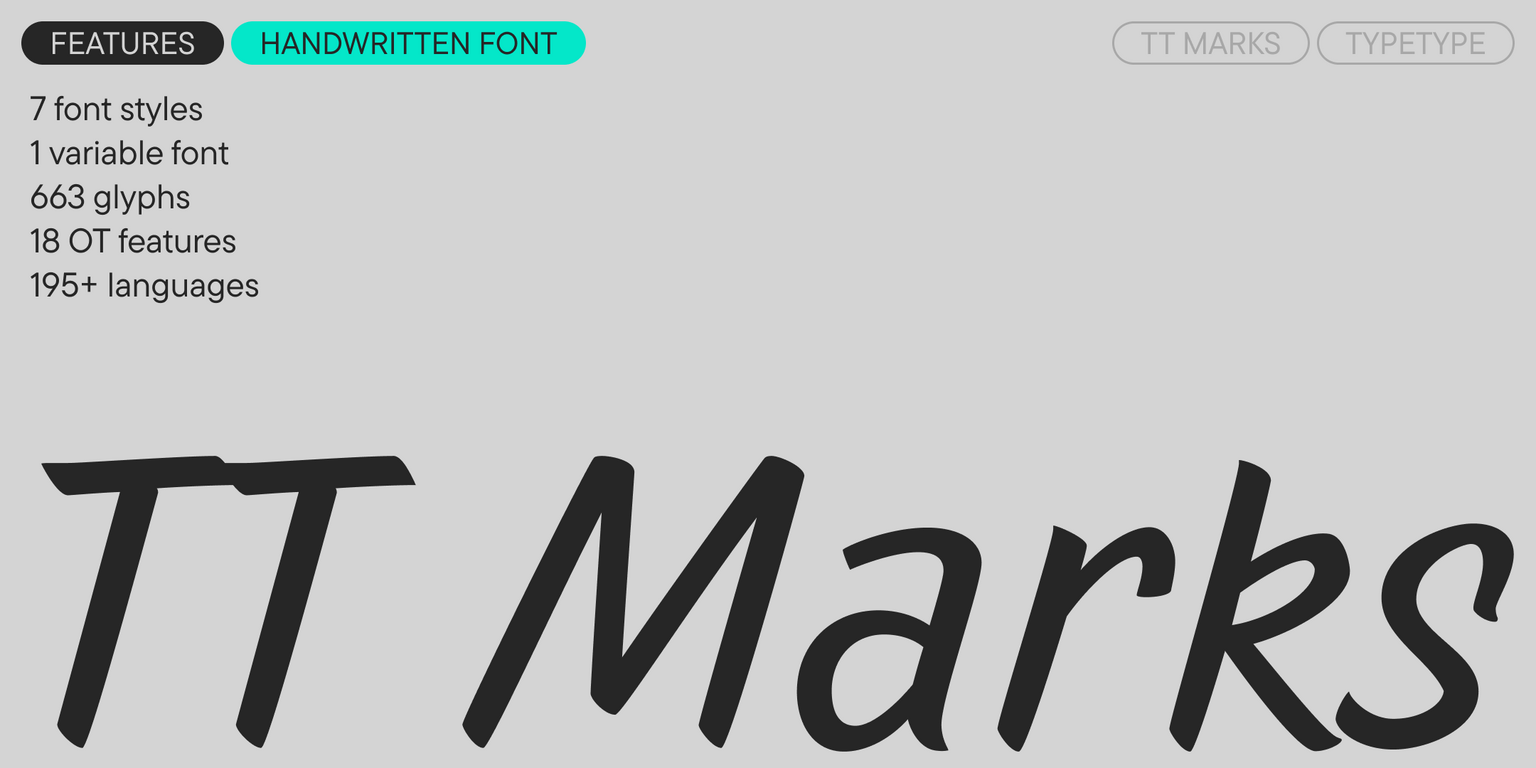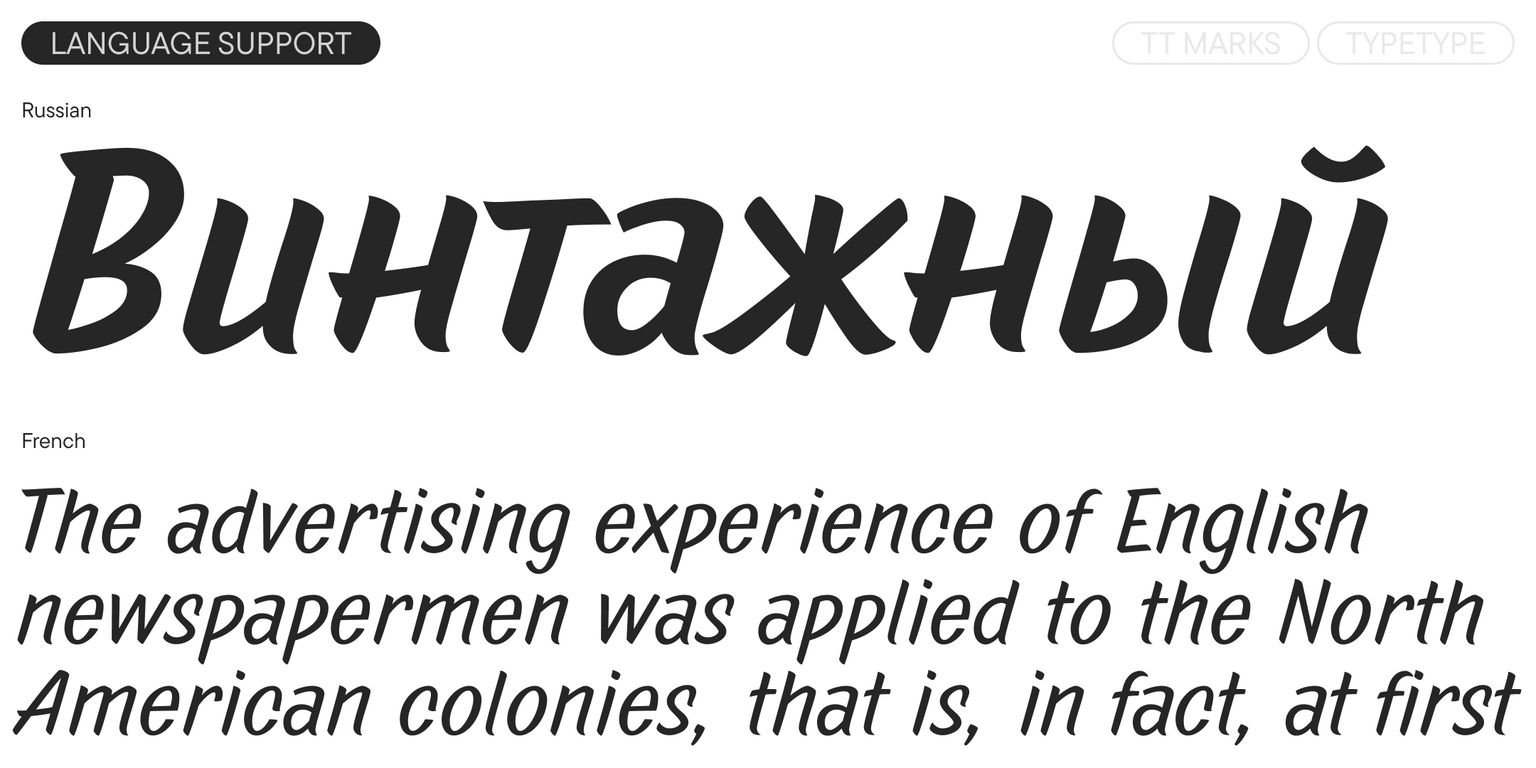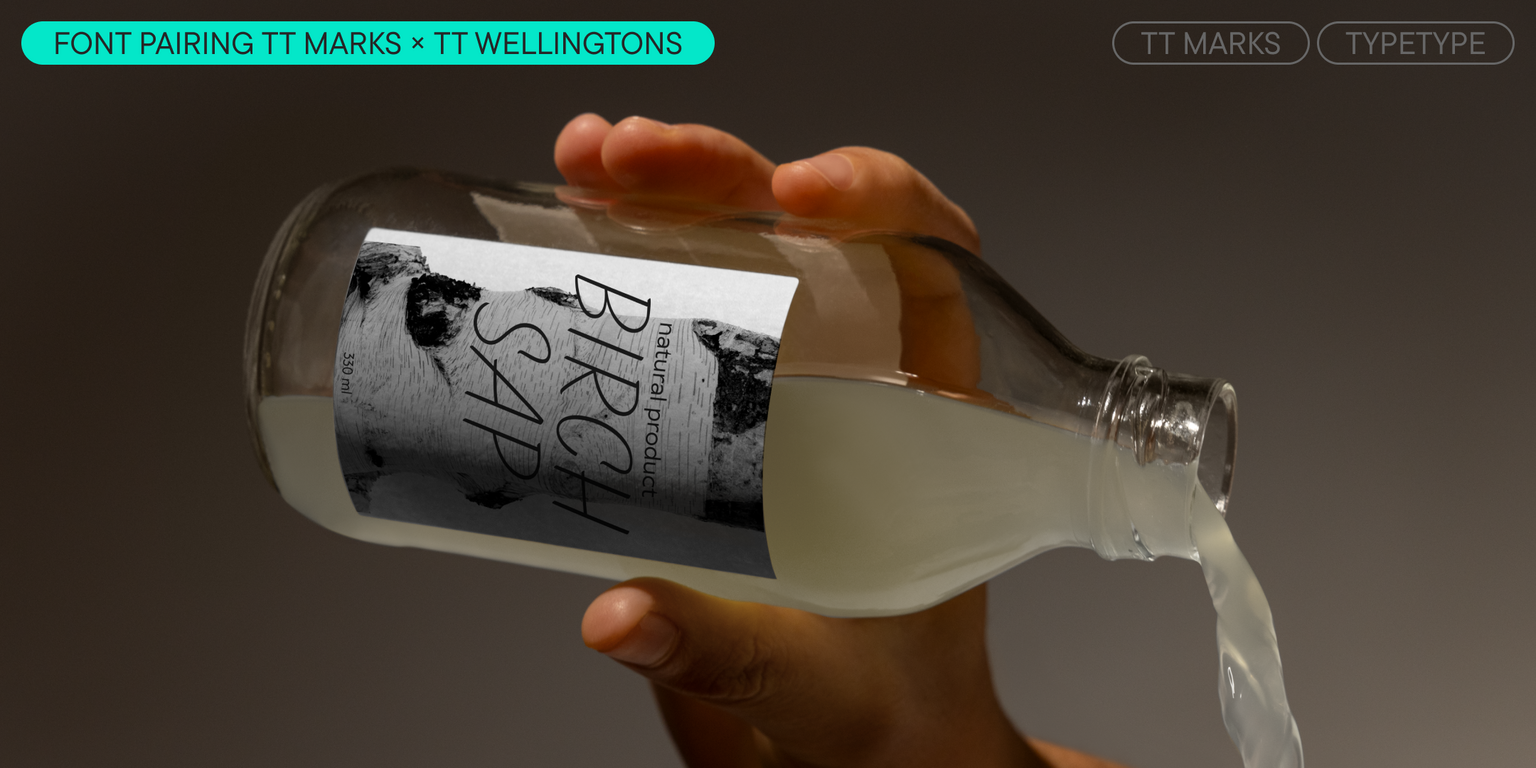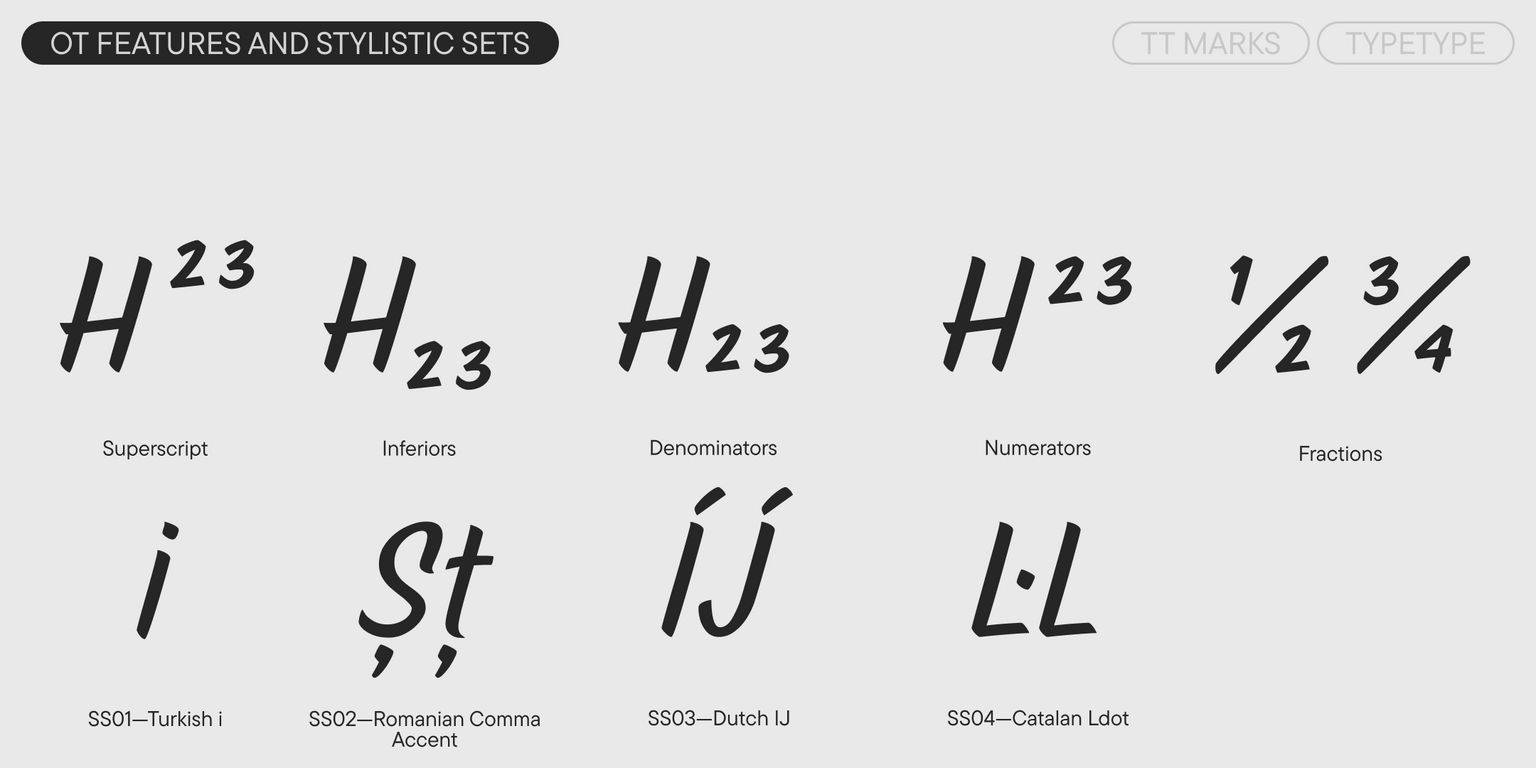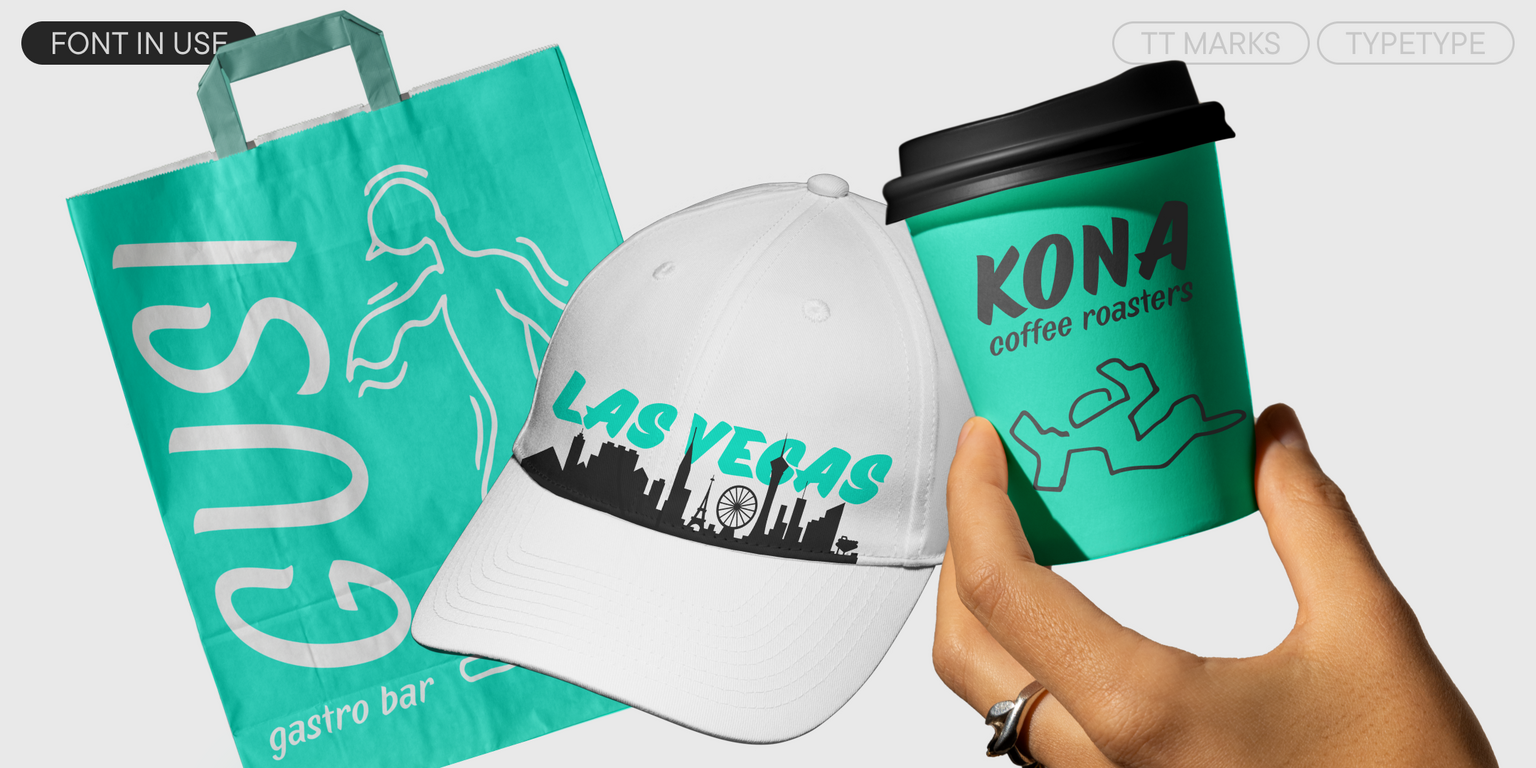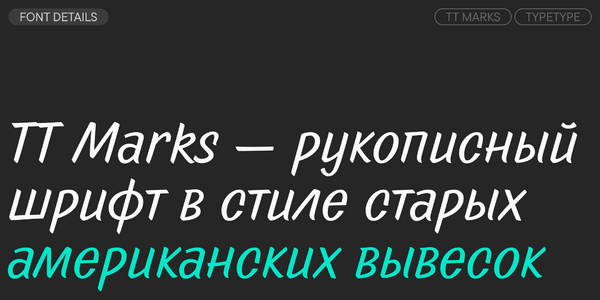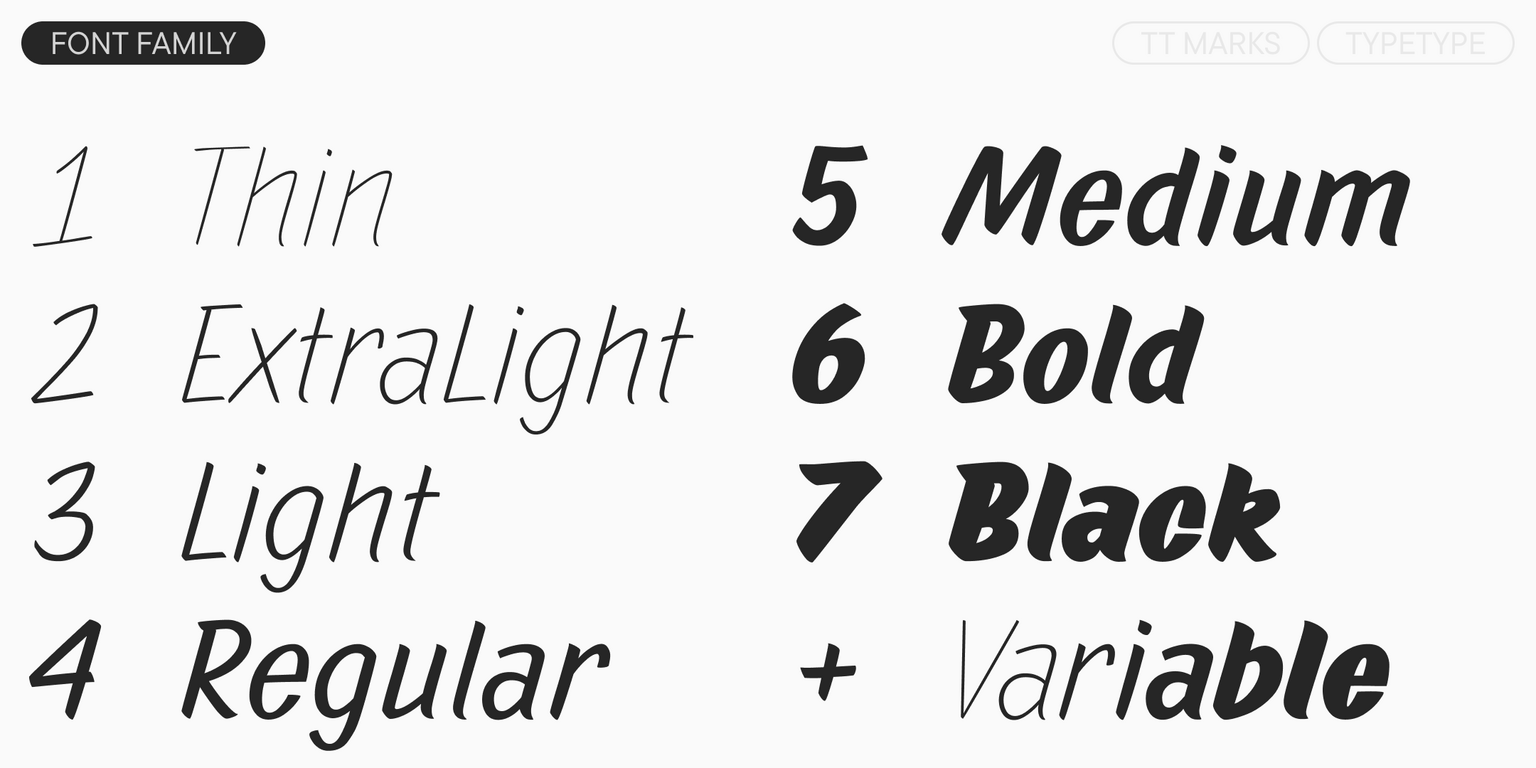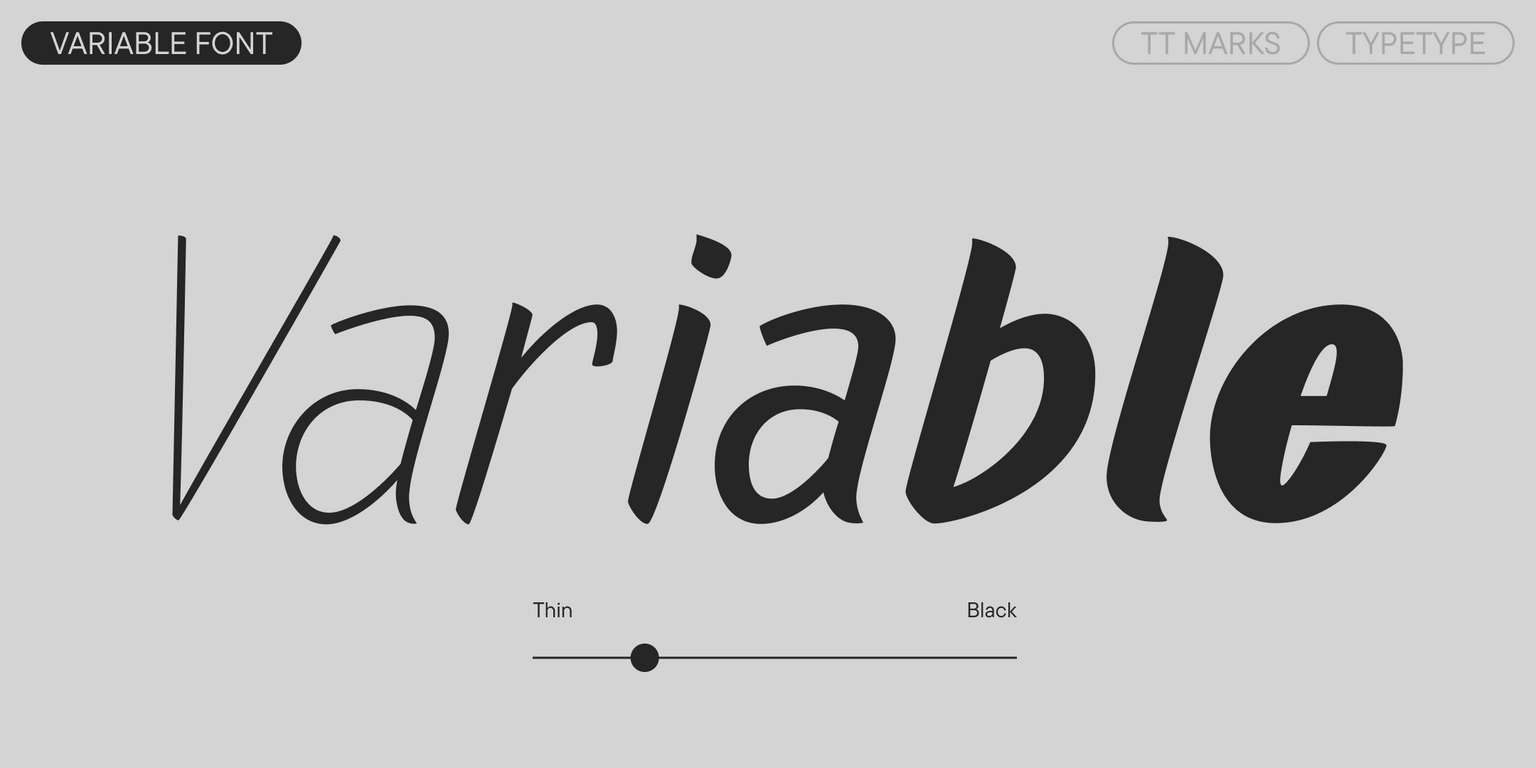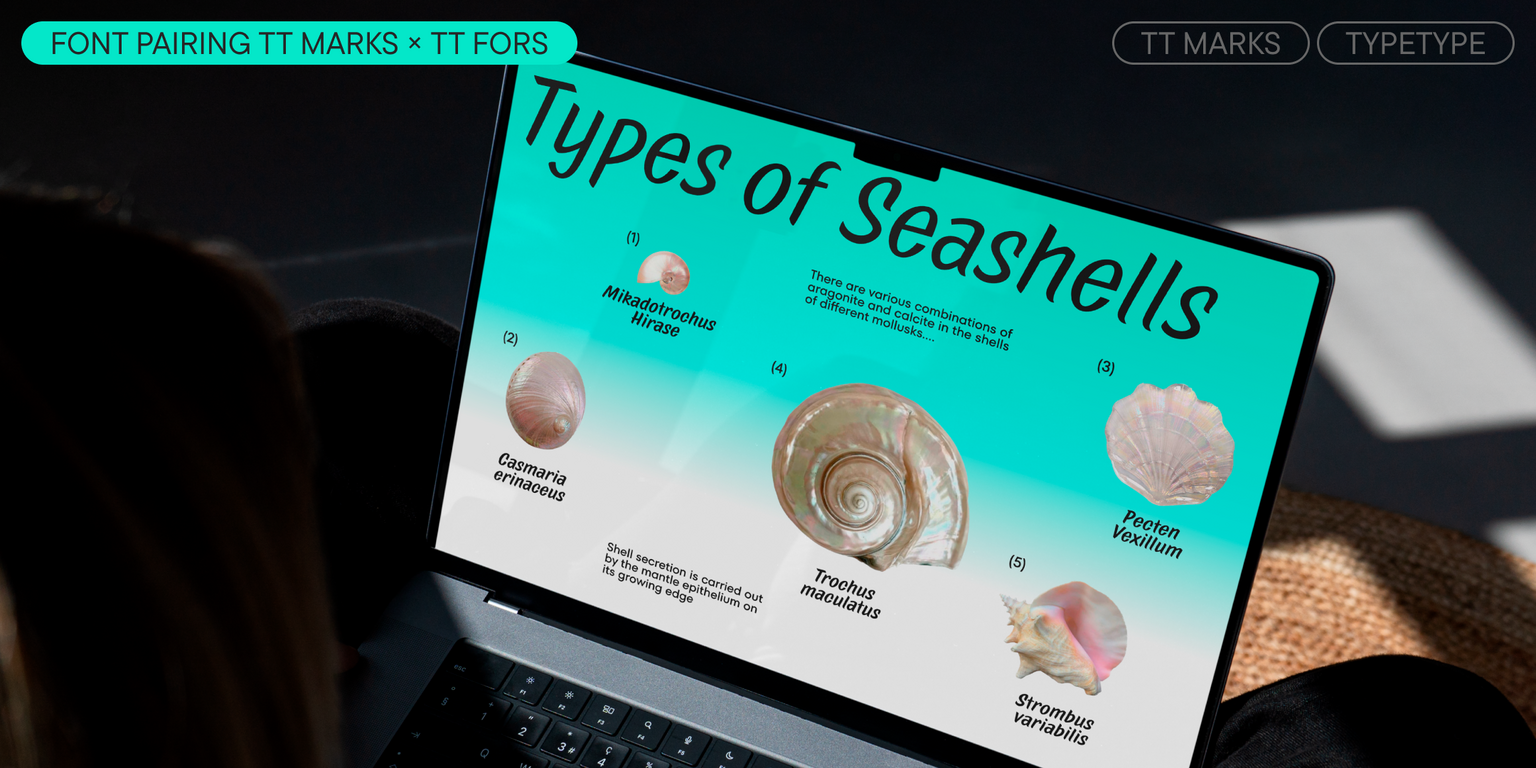
TT Marks
TT Marks — ТТ Маркс
Произносится «ТТ Маркс». «Marks» — множественное число мужского имени Mark. Шрифт назван в честь сына соавтора шрифта. Буквы «TT» являются аббревиатурой названия компании.
TT Marks — декоративный рукописный шрифт с динамичным ритмом. Он вдохновлён классическими американскими расписанными вывесками (sign painting).
TT Marks: шрифт в стиле старых американских вывесок
TT Marks вдохновлен классическими расписными вывесками (sign painting) — теми самыми, которые мастера когда-то создавали кистями прямо на стенах магазинов и кафе. В этом шрифте сохранилась душа ручной работы: живые линии, легкая небрежность и тот самый уличный шарм, который превращал обычные надписи в произведения искусства. TT Marks прекрасно работает в брендинге, придавая логотипам и упаковкам винтажное очарование. В ресторанном меню или кофейных стаканчиках он создает атмосферу уютных американских закусочных. Дизайнеры выбирают его для плакатов, книжных обложек и музыкальных афиш, где важна индивидуальность. Даже в цифровом пространстве — на сайтах и в мобильных приложениях — TT Marks добавляет ту самую человеческую теплоту, которой так не хватает современным экранам. При всей своей аутентичности, он остается удобным и универсальным инструментом для любых проектов.
Семь начертаний от тонкого (Thin) до жирного (Black)
Где применять: афиша, ресторанное меню, книжная обложка, вывеска
О гарнитуре TT Marks
Поддержка языков 190+
Встречайте новый декоративный TT Marks — аутентичный шрифт в стиле старых американских вывесок!
TT Marks — рукописный шрифт с динамичным ритмом, тёплым характером и слегка ностальгическим настроением. Он вдохновлён классическими американскими расписанными вывесками (sign painting), которые когда-то художники создавали вручную с помощью кистей и красок. Сегодня надписи в таком стиле снова набирают популярность.
В рисунке TT Marks сохранилось ощущение рукотворности: живые линии, лёгкая небрежность и неповторимый уличный шарм — всё это делает шрифт самобытным и узнаваемым.
TT Marks прекрасно работает в брендинге и в дизайне упаковки, подходит для оформления обложек книг и журналов, эффектно смотрится в крупном размере — например, на плакатах и афишах. Этот шрифт придаёт любому проекту винтажное очарование, ощущение рукотворности и теплоты. Например, при использовании в айдентике ресторана или кофейни он поможет создать атмосферу уютных американских закусочных.
В TT Marks входит:
• 8 начертаний: 7 прямых и 1 вариативный шрифт, меняющийся по оси жирности;
• 663 знака в каждом начертании;
• 18 OpenType фич;
• Поддержка 195 языков.
TT Marks — дух старых американских улиц, воплощённый в шрифте!
Basic Latin Basic Cyrillic Extended Latin Proportional Lining Figures and Currencies Punctuation and Symbols Math Symbols Arrows
ss02 | Romanian Comma Accent
Şş Ţţ
ss03 | Dutch IJ
ÍJ íj
ss04 | Catalan Ldot
L·L l·l
sups | Superscript
1 2 3
sinf | Scientific Inferiors
1 2 3
numr | Numerator
1 2 3